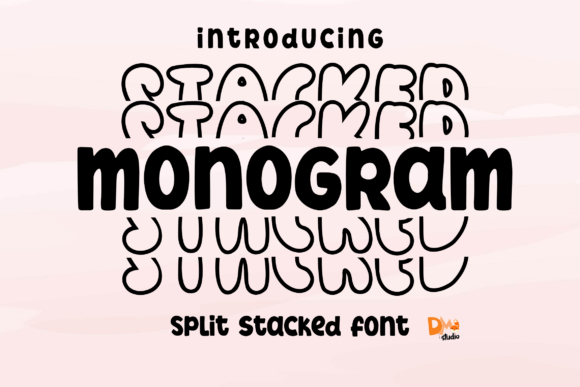
Stacked Monogram
Trovare i giusti elementi di design può essere difficile, ma Stacked Monogram offre una collezione eccezionale che eleva istantaneamente il tuo lavoro.
Realizzato con precisione, Stacked Monogram fornisce vettori puliti, tipografia fluida e una licenza commerciale per la massima tranquillità.
Che tu stia creando prodotti POD (Print on Demand), partecipazioni di nozze o grafiche per i social media, Stacked Monogram è la scelta ideale.